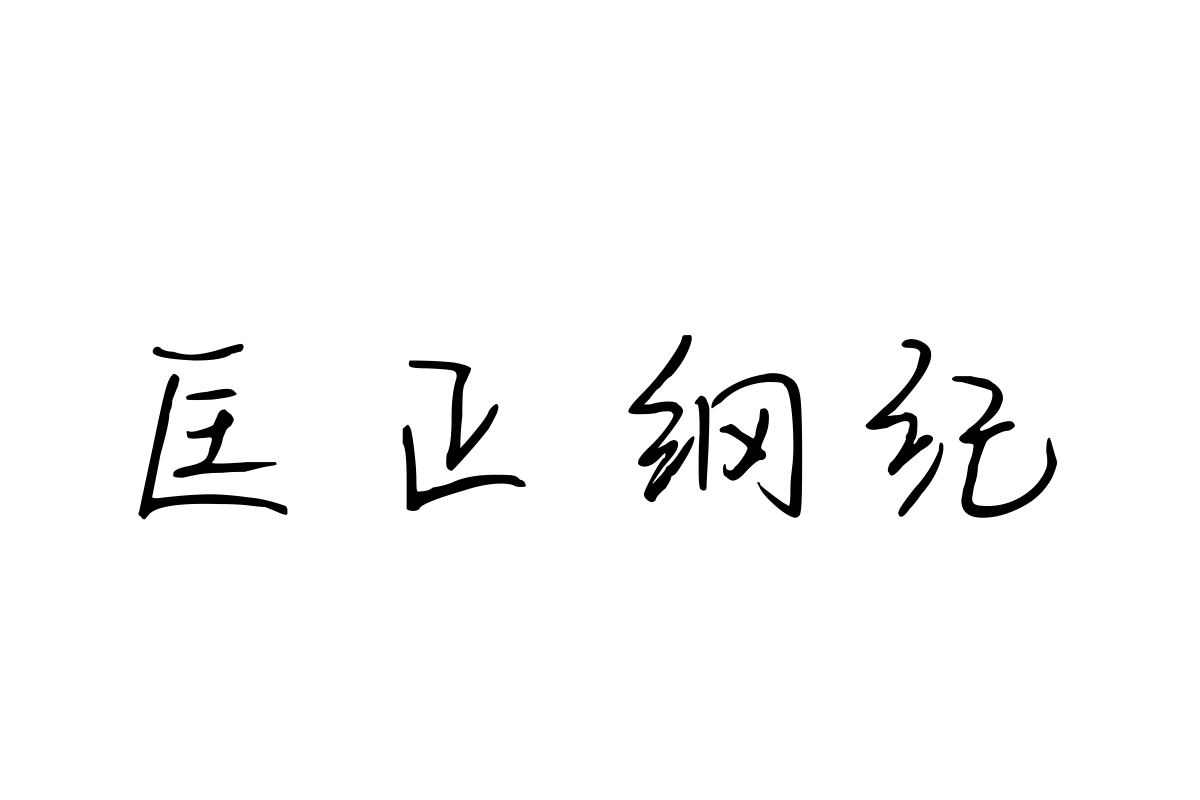
三极文曦行楷字体是一种现代的、具有独特风格的汉字书写风格。它结合了传统的行楷和现代的设计元素,创造出一种既保留了传统韵味又不失现代感的字体。
这种字体的特点是线条流畅、结构严谨,既有行书的灵动性,又有楷书的规整性。它的笔画粗细变化丰富,既有粗犷豪放的一面,也有细腻柔和的一面。这使得它在视觉上呈现出一种独特的美感,既有传统的韵味,又不失现代的时尚感。
此外,三极文曦行楷字体还注重细节的处理,如笔画的角度、粗细的变化等都经过精心设计,使得整个字体看起来更加和谐、自然。
总的来说,三极文曦行楷字体是一种既具有传统韵味又不失现代感的汉字书写风格,适合用于各种需要书写的场合,如书法、设计等。